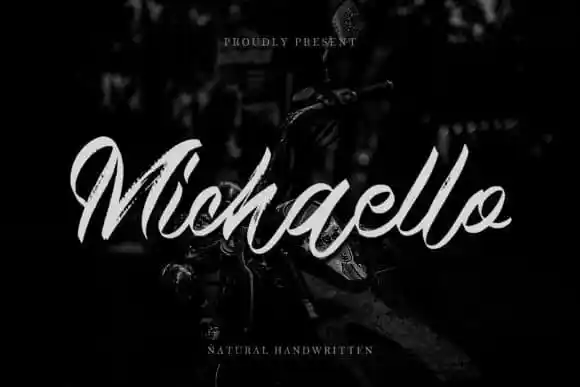
Michaello Brush Font – Download Grátis
A Michaello Brush Font é uma tipografia feita especialmente para quem aprecia a mão-diligente e natural do estilo, sem perder aquela leveza poética que só um texto estilizado pode oferecer. Esta fonte foi criada por Thomas Aradea em 99designs e traz consigo um toque de frescor único e uma textura de caneta impressionante. Ela é perfeitamente adequada para quem busca uma solução casual e natural, que transmite uma sensação amigável e um aspecto deslumbrante do estilo brush. Ideal tanto para designers profissionais quanto para amantes da arte visual, a Michaello Brush Font se destaca pela sua facilidade de uso. O fato de ser PUA (Unicode Private Use Area) codificada significa que você terá acesso a todas as gílias e espaltes sem necessariamente recorrer a um complexo sistema de codificação, tornando o processo muito mais simples e intuitivo. Esta fonte é perfeita para qualquer projeto que busque originalidade e destaque. Sua textura suave e sua aparência natural garantem uma experiência visual única que se assemelha à arte da caneta real, sem ser a mesma coisa – um verdadeiro equilíbrio entre o digital e o humano. É mais do que apenas uma fonte: é uma expressão de quem cria e do momento em que cria, transmitindo sentimentos e emoções através da própria forma. O Michaello Brush Font é a escolha perfeita para aqueles que buscam transparência em sua arte digital.